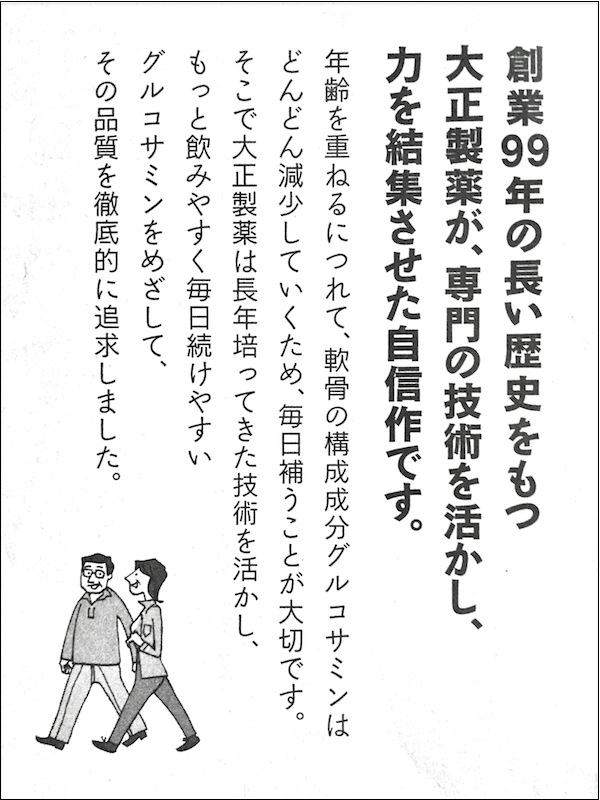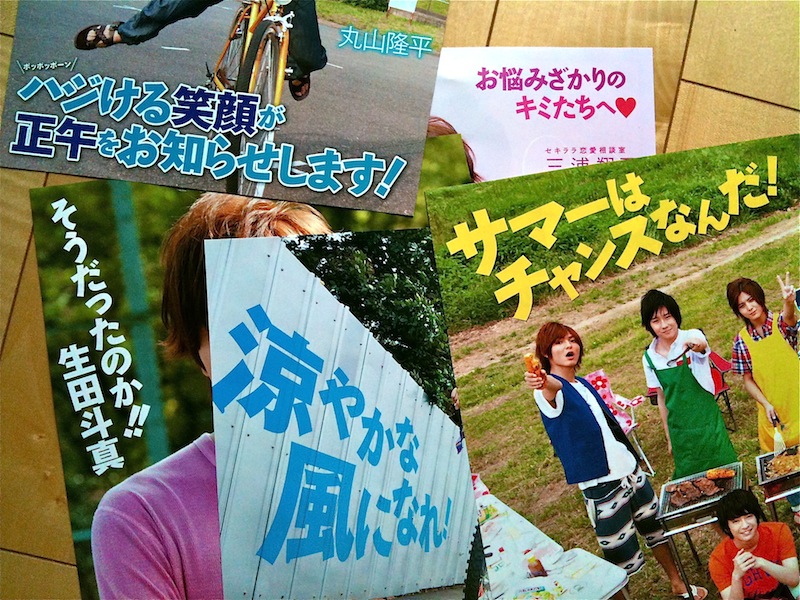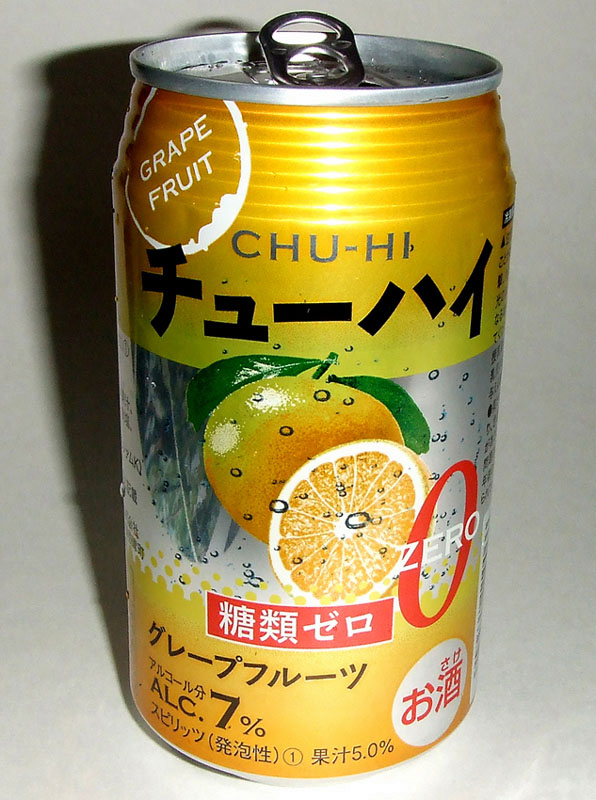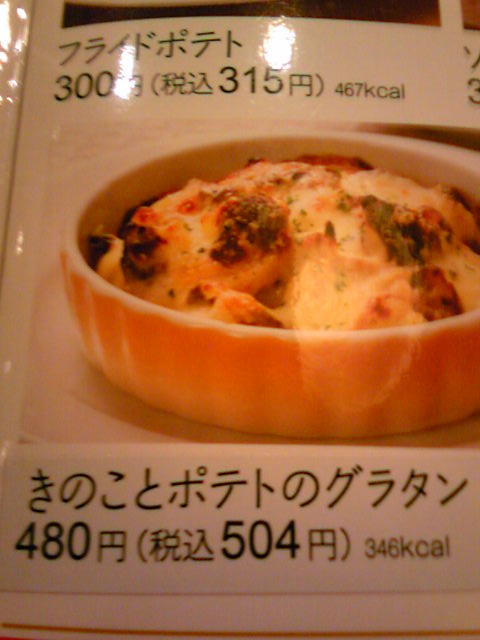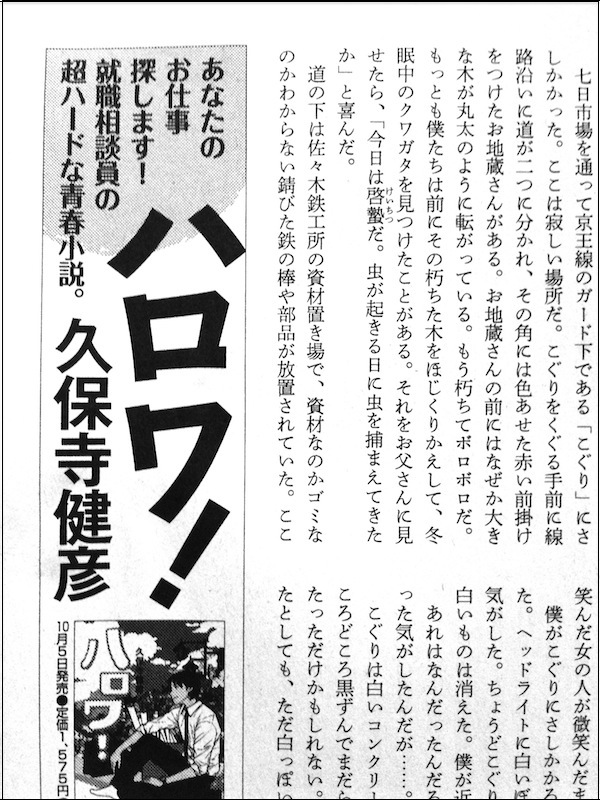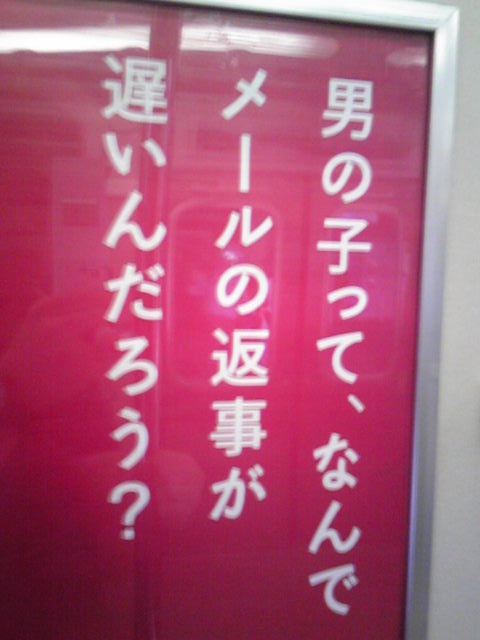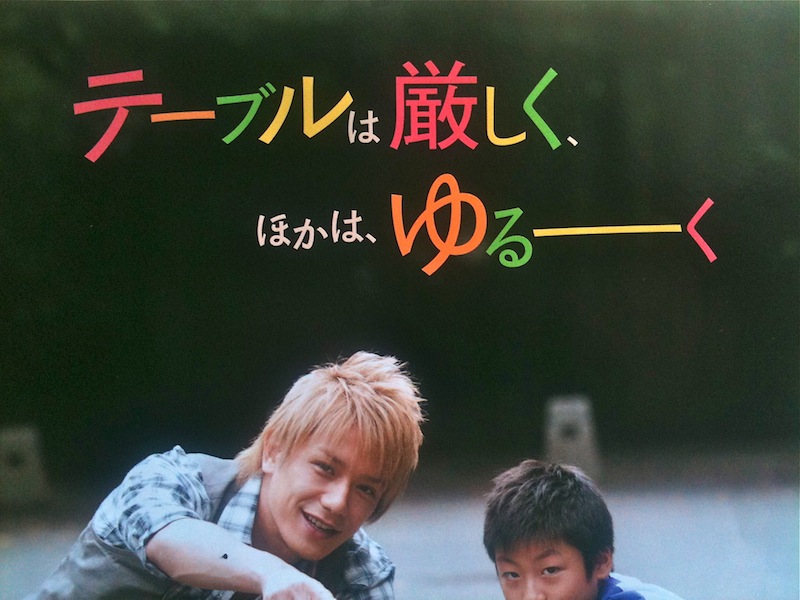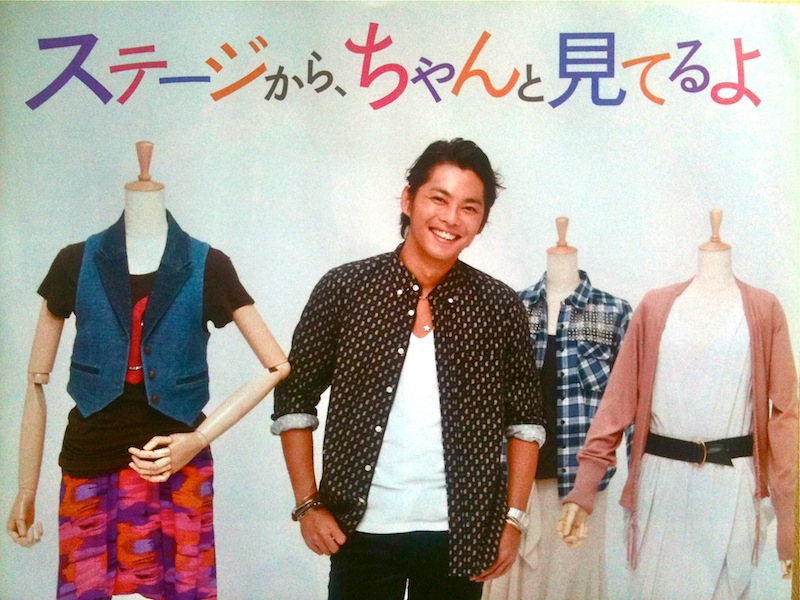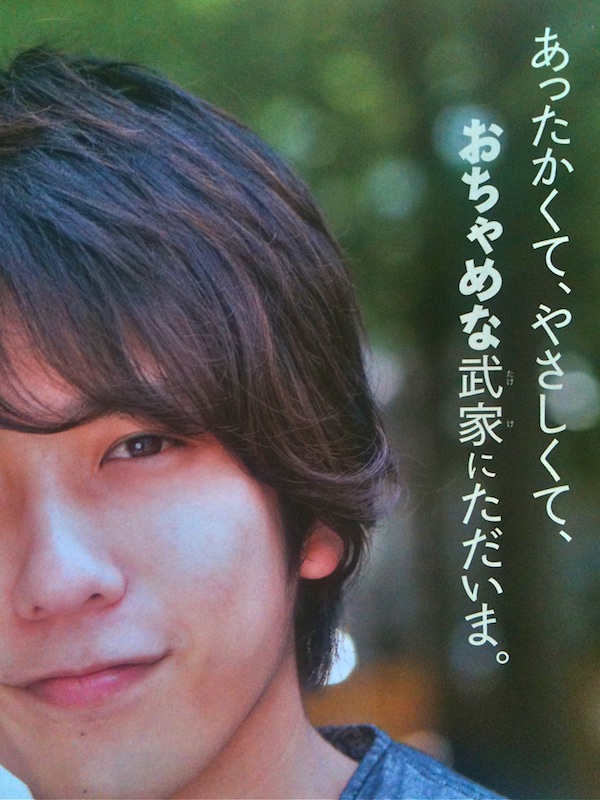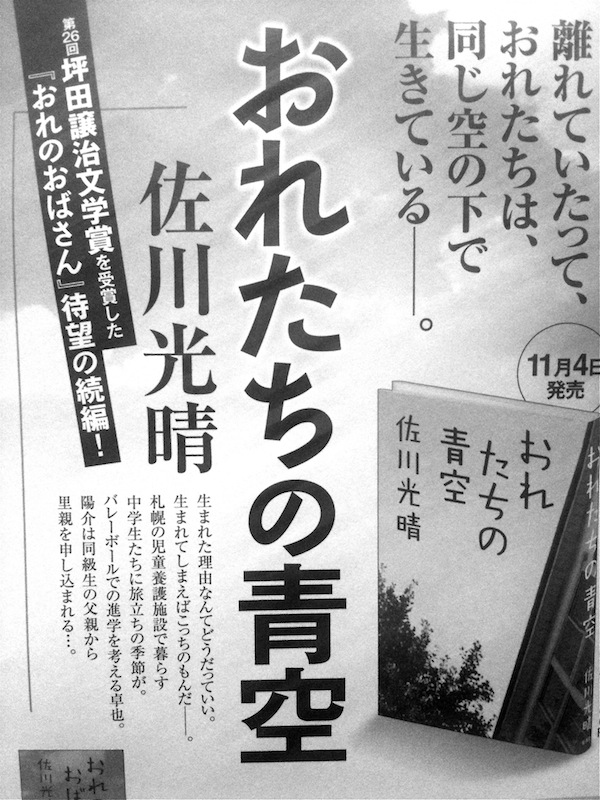
本の表紙  さとうゆたか  2012年8月26日(日) 11:04
書名:きものをリフォーム
著者:高橋恵美子
発行:角川グループパブリッシング
番宣広告  さとうゆたか  2012年8月20日(月) 17:23
新聞に掲載されていたのだったかな?
記事タイトル  さとうゆたか  2012年8月14日(火) 13:43
芸能雑誌の記事です。
雑誌記事タイトル  さとうゆたか  2012年8月1日(水) 9:24
芸能情報誌です。
ラジオ番組のタイトル(radiko)  イワオ ハウス  2012年7月28日(土) 15:12  HP Mail
(見るヒトによるとしても…)
文章であってもロゴ的に使用しても
「スンナリ」感。
さとうゆたか  2012年7月21日(土) 8:40
書名:ともにがんばりましょう
著者:塩田武士
発行:講談社
本の表紙  さとうゆたか  2012年6月25日(月) 21:10
文字の角が丸く処理されています。
書名:ねこもこら
著者:夢路行
発行:秋田書店
本の表紙  さとうゆたか  2012年6月16日(土) 17:16
書名:アコギなのかリッパなのか
著者:畠中恵
発行:新潮文庫
オモチャのパッケージ  さとうゆたか  2012年6月5日(火) 17:07
大阪通天閣のみやげ品売り場で。